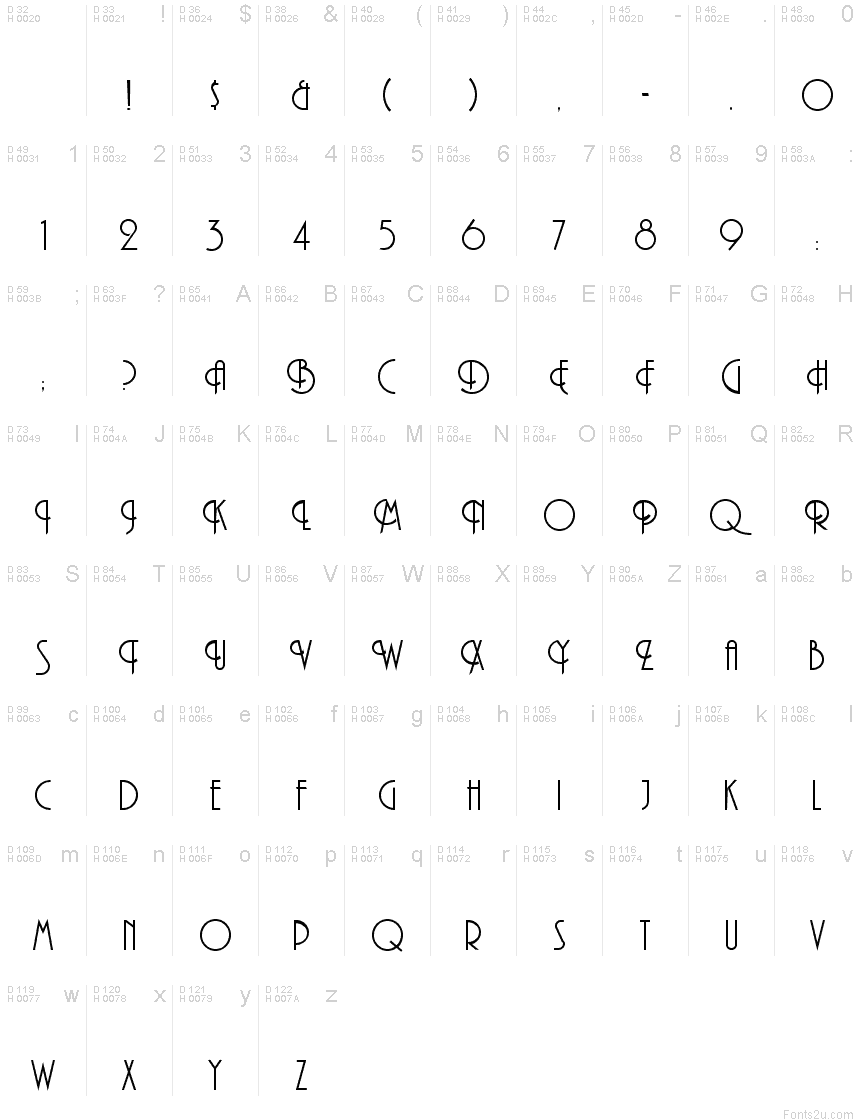
Andes to darmowy krój display w stylu retro, który prowadzi pojedynczy, stabilny skok przez każdą literę, niczym neonowa rurka wygięta w eleganckie geometryczne formy. Wysokie, wąskie litery oraz charakterystyczna zapętlona litera A nadają mu rytm inspirowany stylem Art Déco, podczas gdy zaokrąglone D i S sprawiają, że całość jest przyjazna, a nie chłodna. Efekt przypomina vintage'owe liternictwo z plakatów podróżniczych lub starych szyldów teatralnych, ale w wersji dopracowanej pod nowoczesne ekrany.
Wykorzystując font Andes, tytuły i logotypy zyskują natychmiast odważny, filmowy charakter, który świetnie sprawdza się na plakatach, okładkach albumów, opakowaniach, ulotkach eventowych, w brandingu i grafikach do social mediów. Dzięki spójnej grubości linii, bloki tekstu wyglądają wyjątkowo efektownie, niemal jak zaprojektowany na zamówienie logotyp. Połącz ten darmowy font z prostym bezszeryfowym krojem typu grotesque w tekście głównym i używaj Andes w dużym formacie z dużą ilością światła, aby pozwolić jego wyrzeźbionym krzywiznom i pionowym liniom naprawdę odetchnąć.